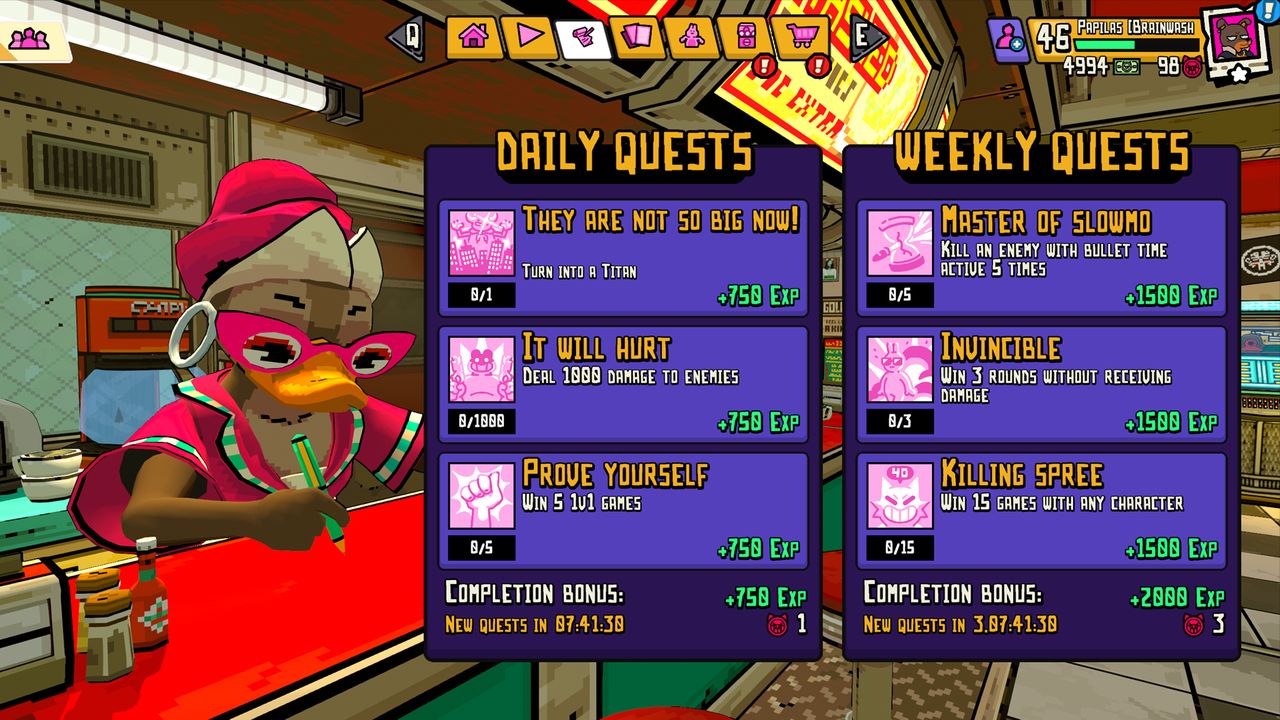
Шрифт «Friendly Fire» для вашей игры
Brainwash Gang выложен для бесплатного скачивания и использования шрифт «Friendly Fire». Это блочный угловой пиксельный шрифт с мультяшным стилем, созданный для игр. Его название представляет собой отсылку к игре, для которой он изначально был создан, «Friends VS Friends».
Имеется языковая поддержка наиболее вероятных для перевода европейских языков, русского и украинского. Лицензия SIL Open Font License позволяет использовать бесплатно, но если вам очень нравится шрифт, пожертвования в авторам приветствуются.